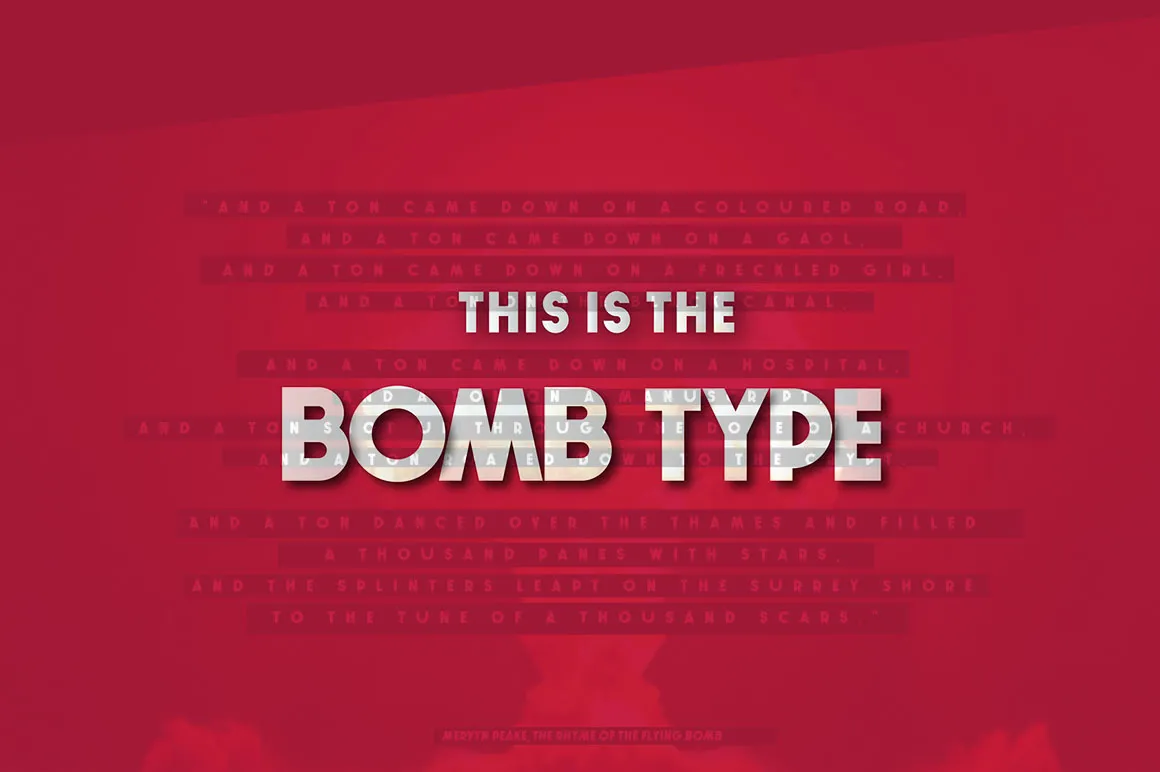
A fonte ‘Bomb Font’ é uma elegante escolha para designers que desejam dar um toque original a suas criações digitais. Desenvolvida pelo designer Hamilton, essa fonte de tipo ganchudo oferece um estilo cool e bold que se encaixa perfeitamente em projetos criativos atuais. Seja você um freelance ou parte da equipe de uma agência de design, esta fonte é um excelente recurso para dar vida a seus novos trabalhos visuais. Descarregue sua versão agora e experimente suas capacidades, certamente não vai se arrepender. Enjoy your bold designs!